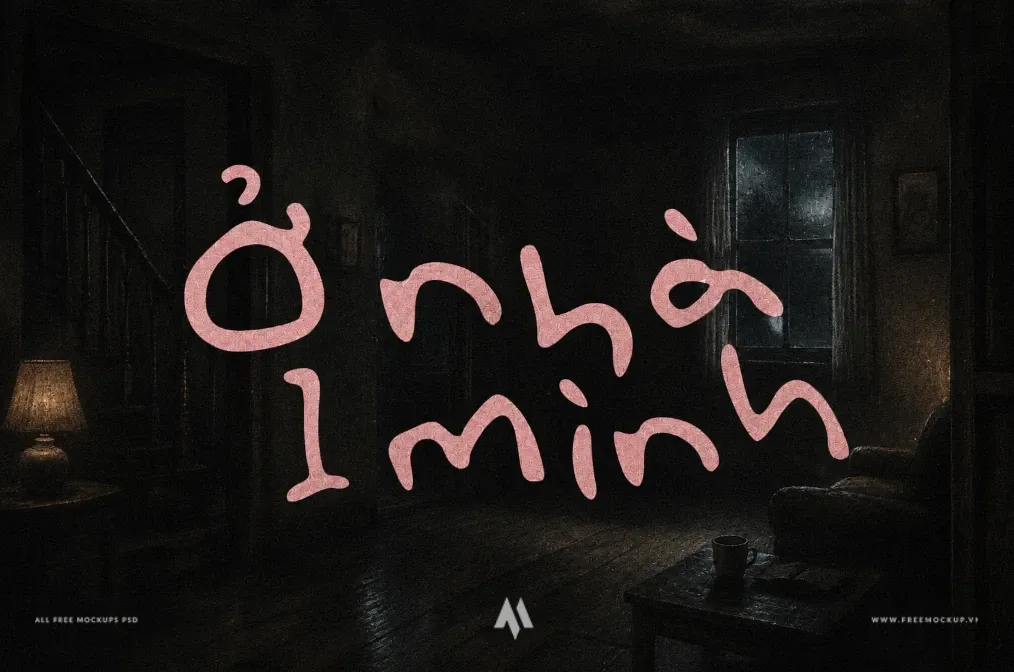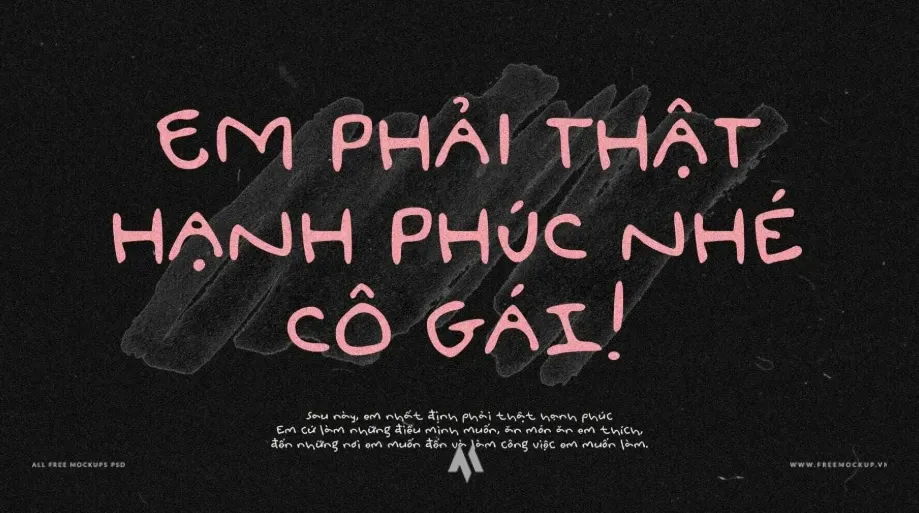
DFVN Purenotes Việt Hóa là bộ font chữ viết tay (Handwritten Font) được tạo tác với mục tiêu tái hiện trọn vẹn nét bút tự nhiên, mộc mạc và chân thực nhất. Với phong cách phóng khoáng, gần gũi cùng độ biến tấu ngẫu hứng cao, bộ font là công cụ lý tưởng để truyền tải trọn vẹn cảm xúc cá nhân và tạo điểm nhấn sống động cho các ấn phẩm thị giác hiện đại.
Đặc điểm nổi bật
- Cảm giác viết tay chân thực: Đường nét tự nhiên, mềm mại và không gò bó, mang lại vẻ ngoài chân phương như được chấp bút trực tiếp trên trang giấy.
- Kho tính năng & Ký tự phong phú: Hỗ trợ đầy đủ chữ hoa, chữ thường, chữ số, hệ thống dấu câu cùng các ký tự thay thế (Alternates) và chữ ghép (Ligatures) linh hoạt.
- Việt hóa ngẫu hứng & Độc đáo: Hệ thống dấu tiếng Việt được xử lý tỉ mỉ với độ biến thiên nhẹ, giữ nguyên tinh thần tự do của chữ viết tay thực thụ mà không lo lỗi font.
Ứng dụng đa dạng trong thiết kế
- Sáng tạo nội dung số (Video & Reels): Chèn phụ đề, tiêu đề, typography cho video ngắn trên TikTok, YouTube Shorts, Instagram Reels và vlog du lịch/đời sống.
- Truyền thông & Mạng xã hội: Thiết kế hình ảnh trích dẫn (quotes), bài đăng truyền cảm hứng, infographic chia sẻ kiến thức và thumbnail video.
- Ấn phẩm sự kiện & Đời sống: Thiệp mời, bưu thiếp, thiệp chúc mừng, nhật ký số (digital journal), planner và sticker trang trí.
- Nhận diện & Bao bì phong cách mộc: Logo cá nhân, nhãn dán sản phẩm handmade, menu quán cafe và bao bì quà tặng thủ công.